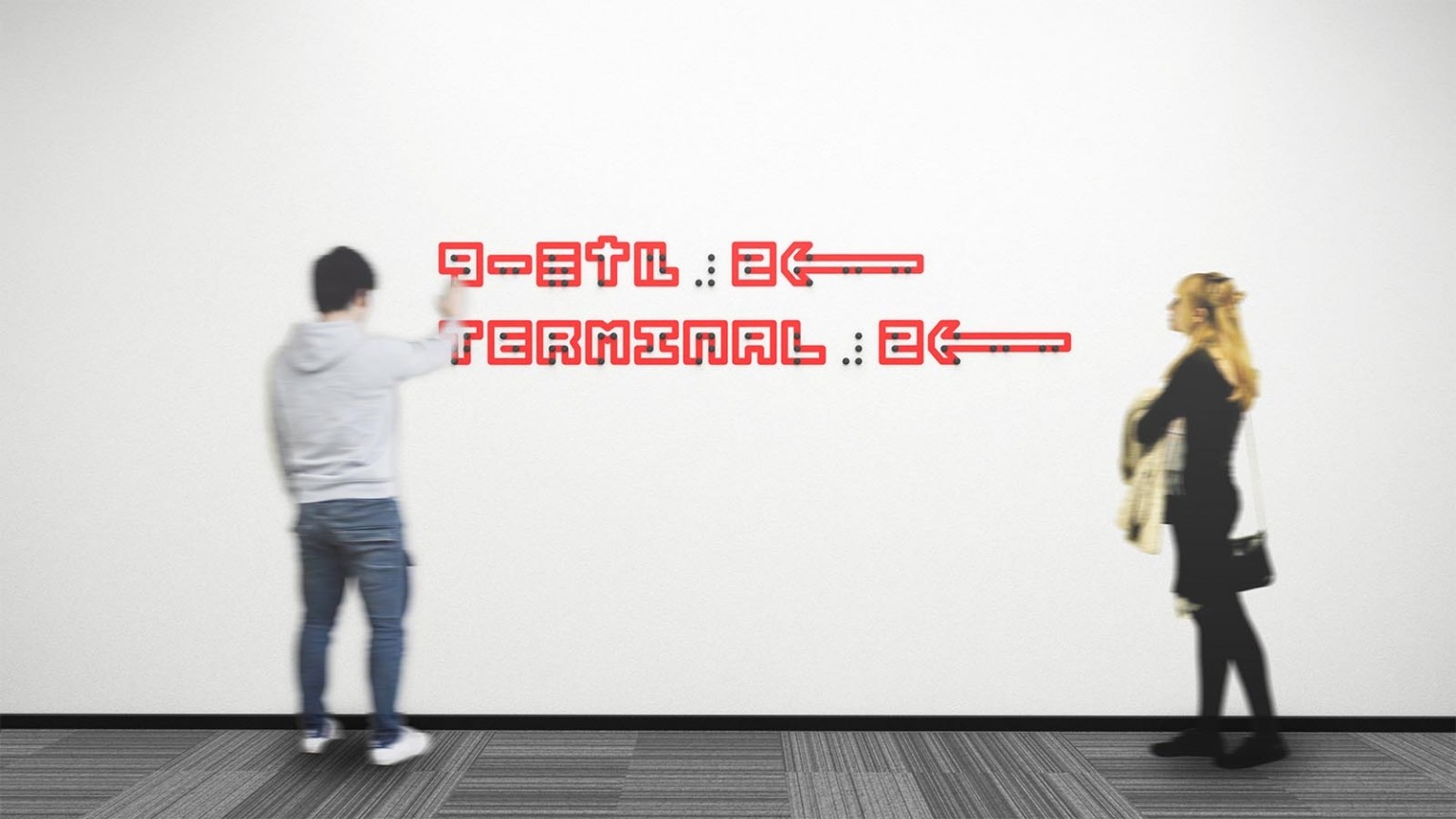
¿Cómo podría leer el sistema Braille con la vista y no solo con el tacto?
Esa fue la pregunta que se hizo el diseñador japonés Kosuke Takahashi. Y es así cómo decidió crear Braille Neue. Una tipografía que combina las letras del abecedario en inglés y japonés, con los puntos de cada letra Braille.
Al ver que no existía un vínculo entre las formas, desarrolló una fuente que se adaptara al sistema Braille y que sea de fácil legibilidad. Su objetivo era lograr que tanto videntes como no videntes, entenderían el mismo mensaje.
Después de una extensa investigación y varios ejercicios, logró diseñar cada letra basándose en los puntos del Braille. Esto se puede ver fácilmente en las letras J, T, V y Z de su tipografía. Además, creó 2 diseños: Standard para el alfabeto en inglés y Outline, para escribir kanjis japoneses.
Takashi no es el primero en combinar una tipografía con los puntos braille, pero sí en incluir el lenguaje japonés.
El siguiente paso para Kosuke Takahashi:
Kosuke desea implementar la tipografía en los Juegos Paralímpicos de Tokio en 2020, su ciudad natal. Según cuenta en su micrositio quiere «crear un verdadero espacio universal donde cualquiera pueda acceder a información».
Actualmente, el sistema Braille no está implementado en espacios públicos ya que para hacerlo, se necesita espacio adicional y muchos no lo consideran importante. Braille Neue se pronuncia ante esta problemática al hacer que el Braille sea de fácil lectura para las personas videntes. Al difundir este nuevo lenguaje, creo que muchas personas se sentirán familiarizadas y existirá la posibilidad de expandirnos a través de señales públicas.
Aunque sigue en etapa de desarrollo, Braille Neue tiene altas expectativas. Esperemos que este sea el comienzo de una nueva era de comunicación donde se combinen ambos mundos: el lenguaje que conocemos y el Braille.